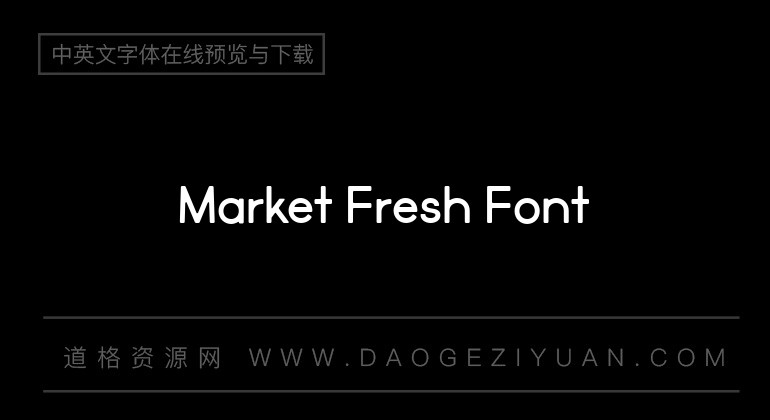
Market Fresh Font
Market Fresh Font 字体是一种现代风格的字体,它具有清晰、简洁、时尚的特点。该字体的设计灵感来自于市场和商店标志牌上使用的手写字体,因此它的字母形状和笔画都带有一些手写风格的特征。 该字体包含大小写字母、数字、标点符号和一些特殊符号,可以用于各种设计场景,如商标设计、海报设计、包装设计等。该字体的不同字母之间的间距非常适中,使得阅读体验非常好。 总的来说,Market Fresh Font 字体是一款非常适合现代设计风格的字体,它简洁、时尚,同时具有一定的手写感,可以为设计作品增添一份独特的魅力。
Market Fresh Font是一款非常不错的手写艺术字体,具有很好的视觉感,适合于文化类的宣传设计、商业类品牌的广告和产品包装设计以及个性化文字排版等较多场景。